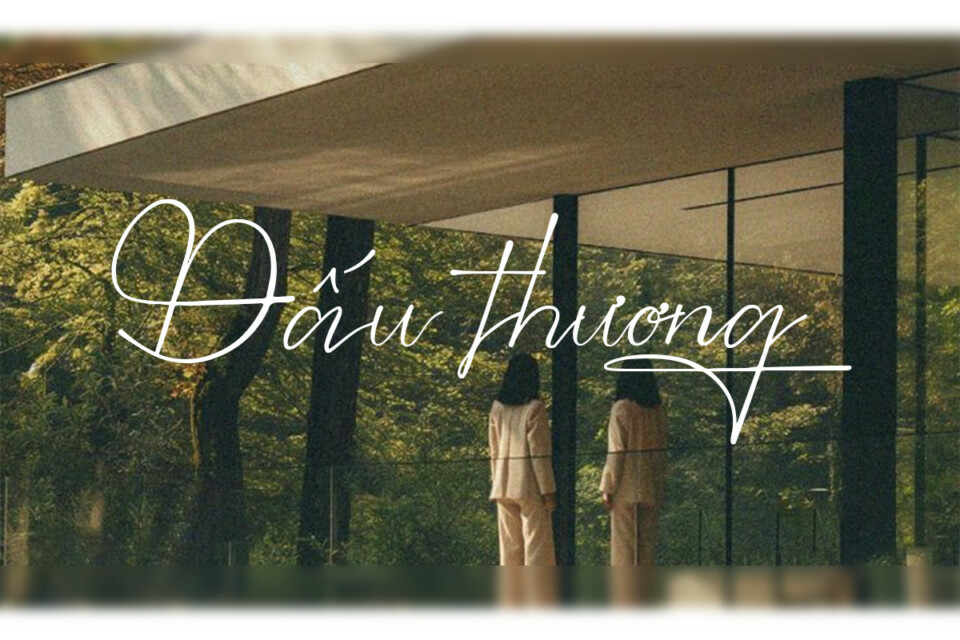
Font việt hoá MJ Betrayos – Nghệ thuật Typography cổ điển và tinh tế cho thiết kế của bạn
Giới thiệu về Font việt hoá MJ Betrayos
Trong thế giới đồ họa hiện đại, việc tìm kiếm một bộ Font Chữ vừa mang nét cổ điển vừa đáp ứng được nhu cầu thẩm mỹ là điều vô cùng quan trọng. Font việt hoá MJ Betrayos chính là sự lựa chọn hoàn hảo dành cho những ai yêu thích phong cách sang trọng và lãng mạn. Với các đường nét thanh mảnh nhưng chắc chắn, bộ font này mang đến một luồng gió mới cho cộng đồng thiết kế tại Việt Nam. MJ Betrayos không chỉ là một phông chữ thông thường mà còn là một tác phẩm nghệ thuật, giúp truyền tải thông điệp một cách tinh tế và giàu cảm xúc hơn.
Đặc điểm nổi bật của Font việt hoá MJ Betrayos
Bộ Font việt hoá MJ Betrayos được thiết kế với các ký tự bay bổng, có độ tương phản cao giữa các nét thanh và nét đậm. Điều này tạo nên sự cân bằng tuyệt đối, giúp văn bản trở nên dễ đọc nhưng vẫn giữ được vẻ đẹp quý phái. Đặc biệt, bản việt hóa đã được tối ưu hóa hoàn toàn để hiển thị chính xác các dấu tiếng Việt, đảm bảo không bị lỗi font khi soạn thảo văn bản hay thiết kế trên các phần mềm chuyên dụng như Photoshop, Illustrator hay Canva.
Ứng dụng thực tế của Font việt hoá MJ Betrayos
Nhờ vẻ ngoài lịch lãm, Font việt hoá MJ Betrayos thường được các nhà thiết kế ưu tiên sử dụng trong các dự án đòi hỏi tính thẩm mỹ cao. Bạn có thể dễ dàng bắt gặp bộ font này trên các thiệp mời đám cưới, bìa sách nghệ thuật, hoặc các banner quảng cáo thời trang cao cấp. Ngoài ra, nó cũng rất phù hợp để làm logo thương hiệu cá nhân hoặc tiêu đề tạp chí, giúp tạo ấn tượng mạnh mẽ ngay từ cái nhìn đầu tiên với người xem.
Lưu ý khi sử dụng trong học tập và công việc
Đối với học sinh và giáo viên, việc sử dụng Font việt hoá MJ Betrayos trong các bài thuyết trình hay thiết kế báo tường sẽ giúp bài làm trở nên chuyên nghiệp và sinh động hơn. Tuy nhiên, bạn nên lưu ý sử dụng font này cho các tiêu đề lớn hoặc các đoạn trích dẫn ngắn để đạt hiệu quả thị giác tốt nhất, tránh dùng cho các đoạn văn dài để người đọc không bị mỏi mắt.